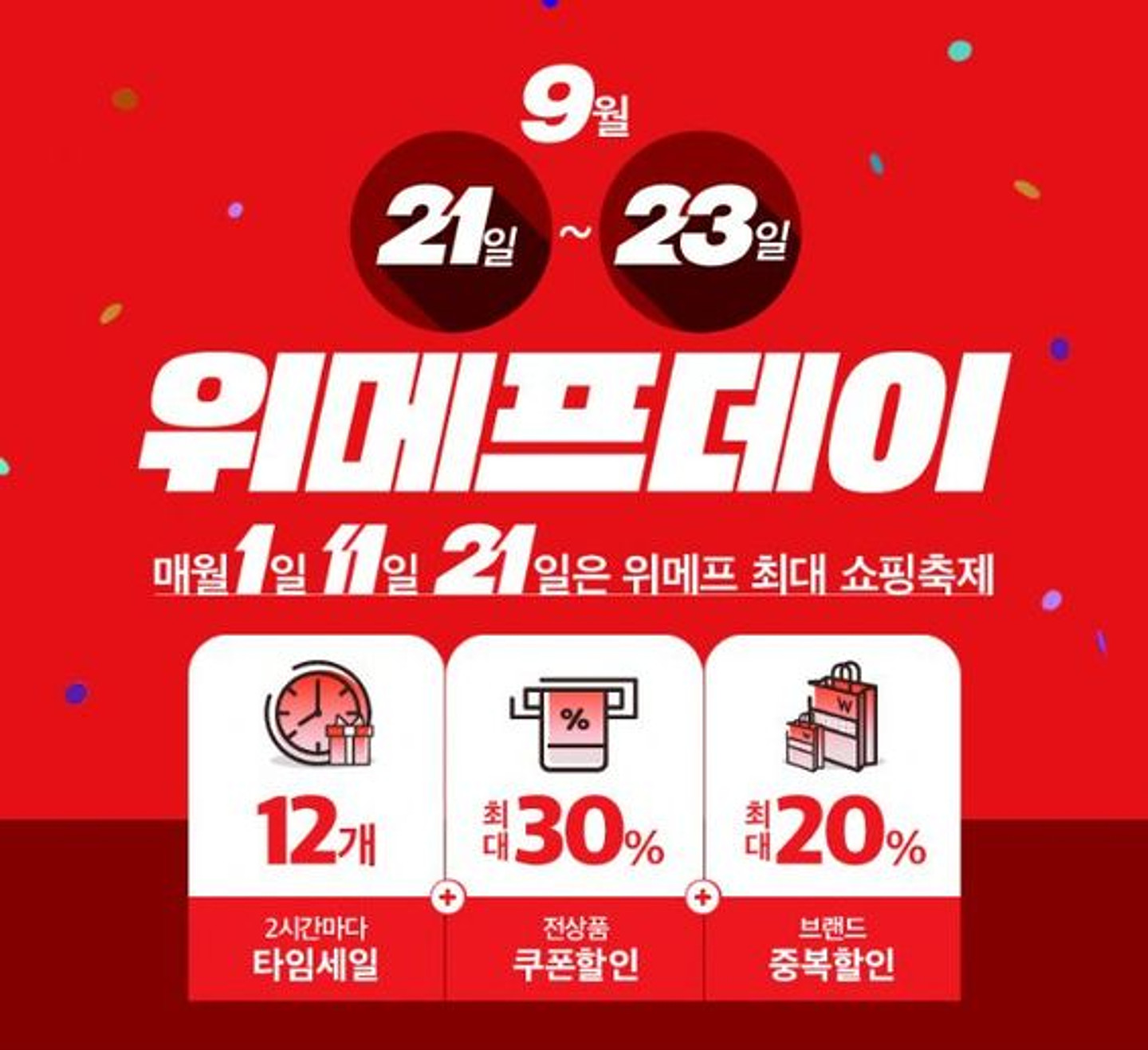
위메프데이 폰트뭔가영
Sandoll 프레스 01 Original
Sandoll 프레스
산돌 프레스는 시대의 거울 프로젝트의 네 번째 결과물 쉴 새 없이 생산되며 발전하는대중문화의 속도감을 표현한 폰트이다. 무게감이 느껴지는 꽉찬 획과 개성있는 복합모임꼴, 넓고 낮은 모습의 자폭, 그리고 무엇보다 대량생산의 속도감이 느껴지는 기울기가 특징이다.